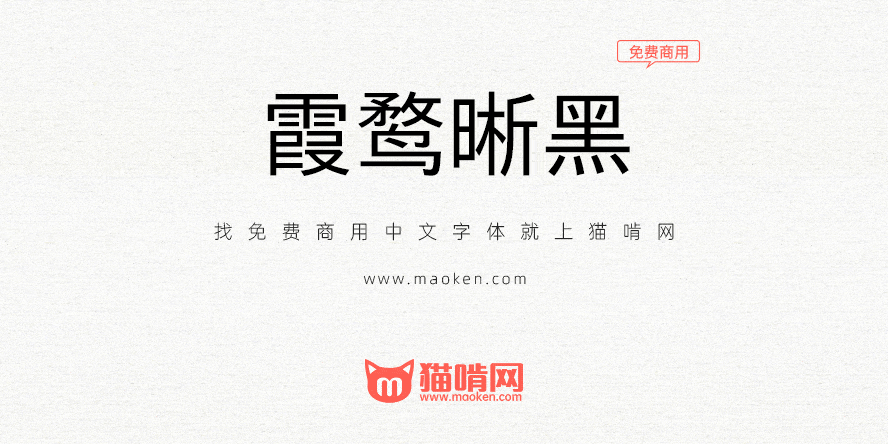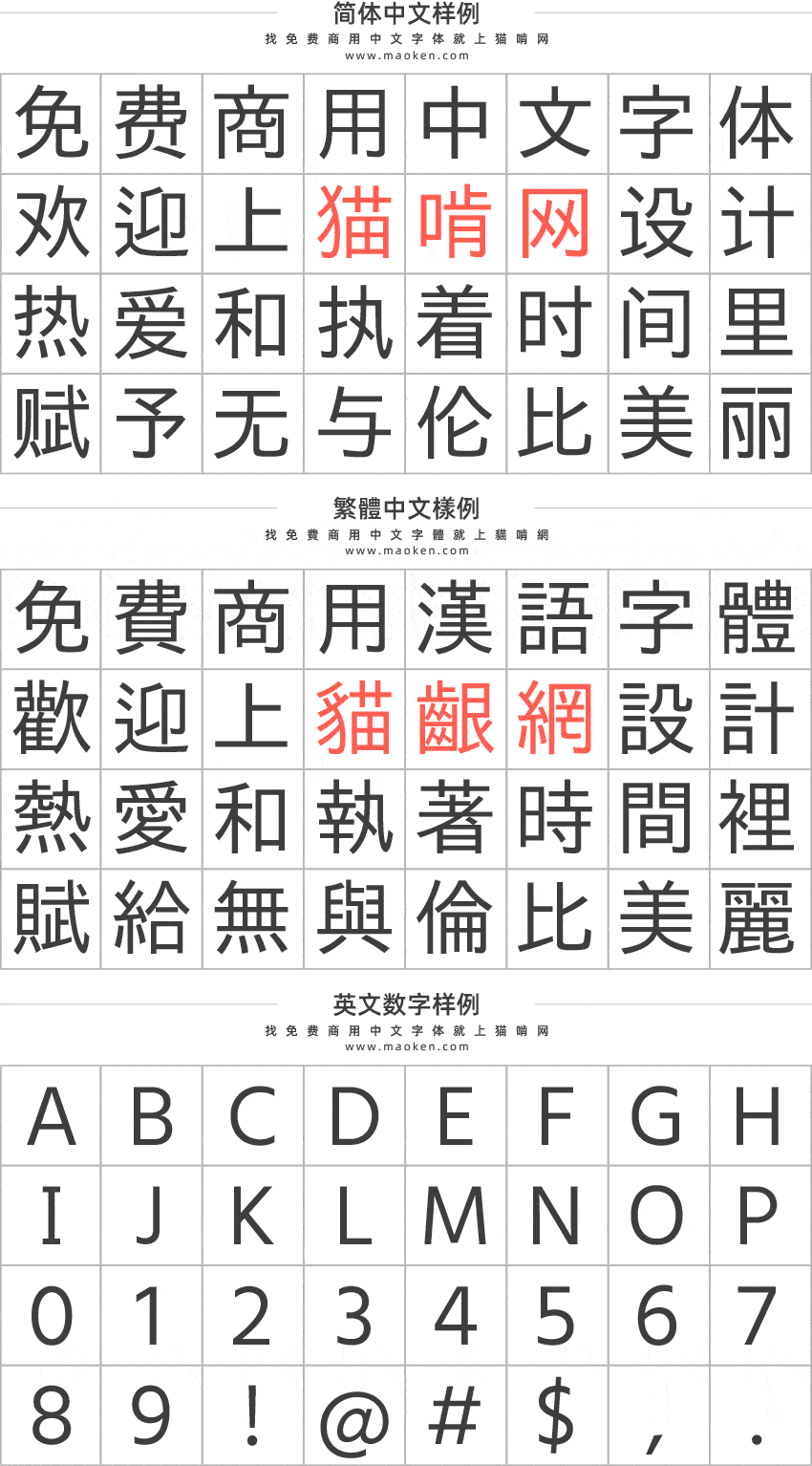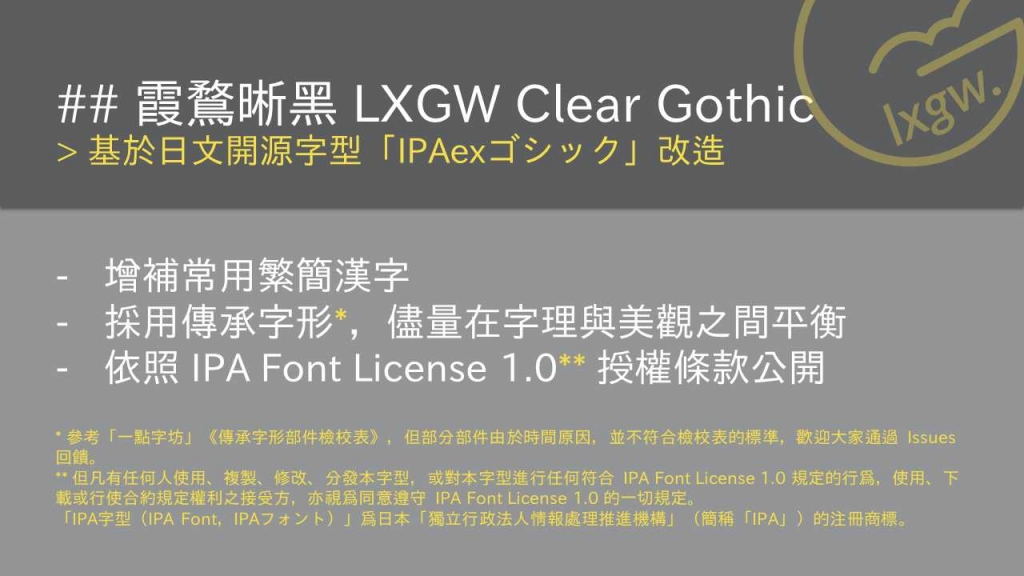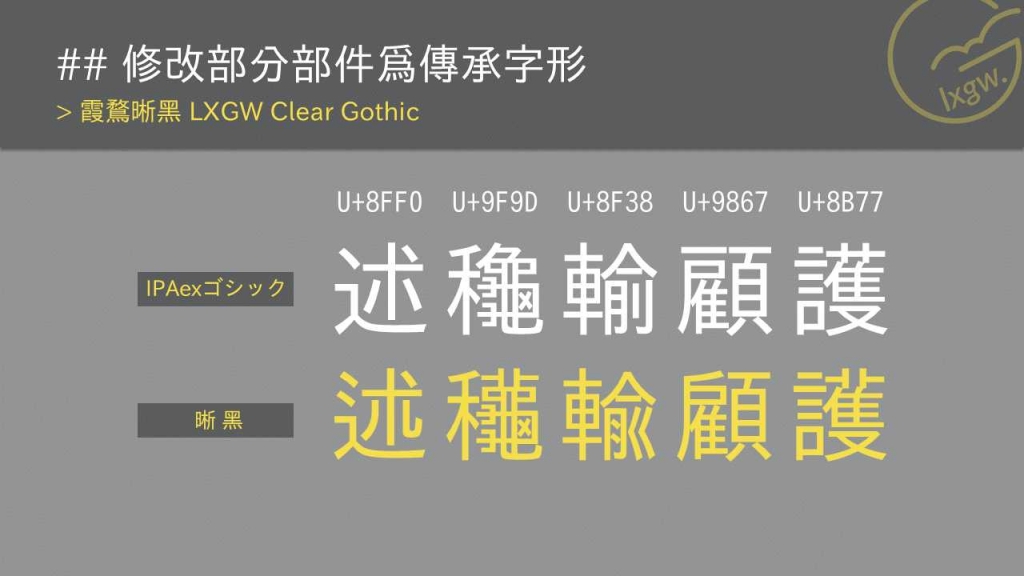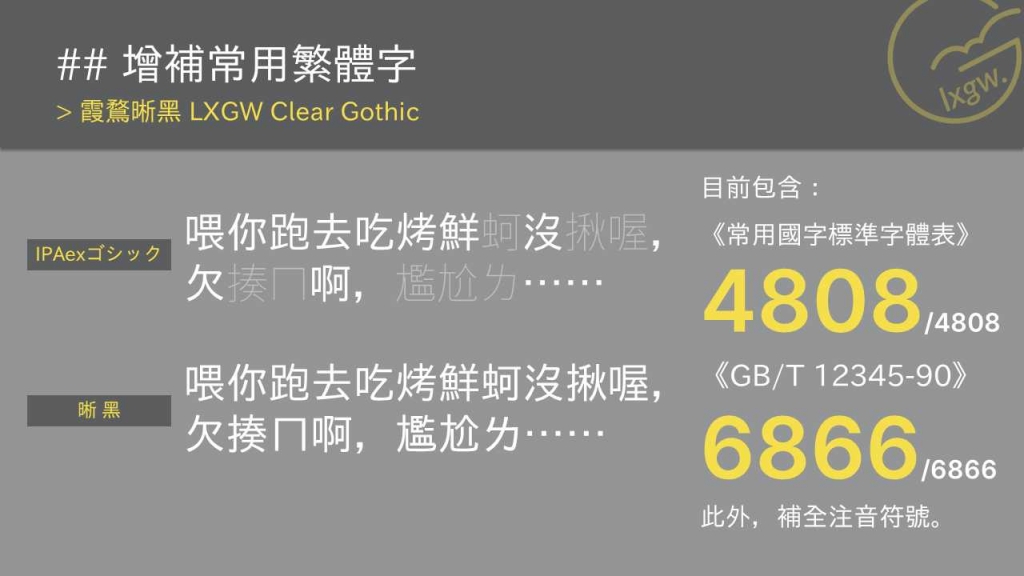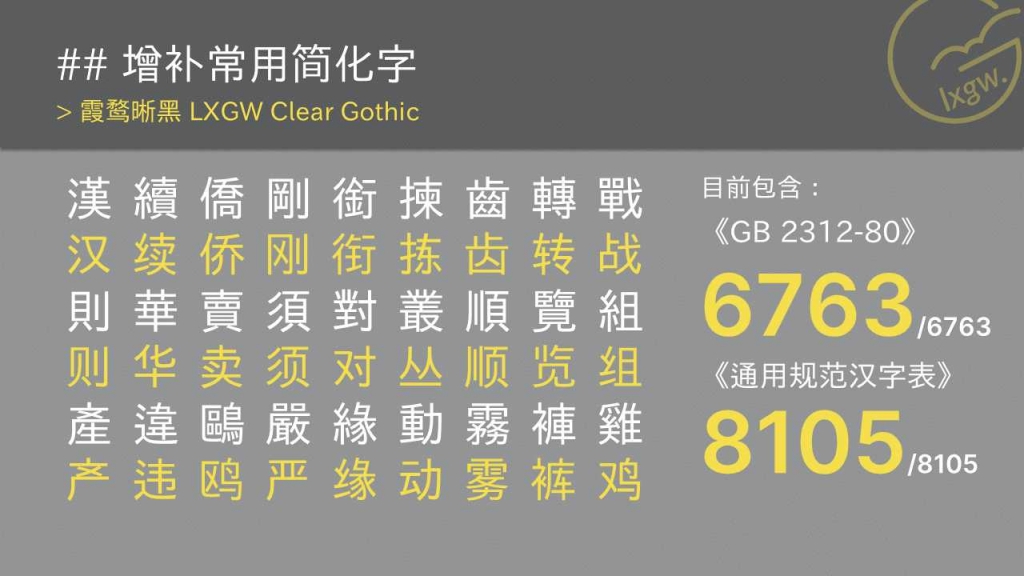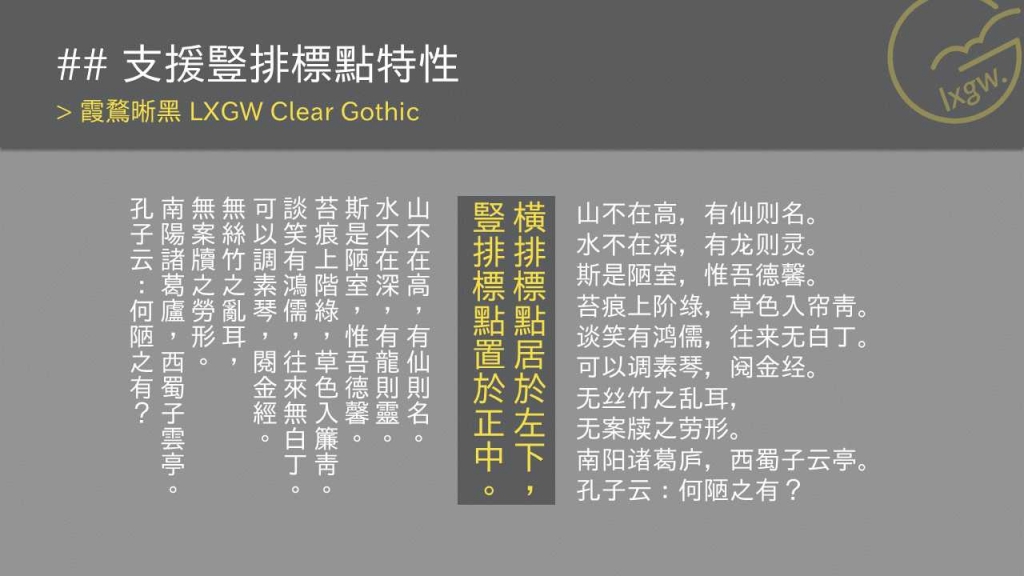
霞鹜晰黑:一款衍生于IPAex黑体的免费中文字体 更精致更清晰
一、项目简介
2009 年,日本IPA以符合Open Source Initiative开源定义的「IPA 开放字型授权条款」,发布两款「IPA 字体」,包括 「IPA 明体(IPA 明朝)」及「IPA 黑体(IPA ゴシック)」。字体衍生自林隆男(Takao Hayashi)所设计的两款字体:TypeBank 公司的「TB 明体」和「TB 黑体」。字体包含的日本常用的字符,供日本用户使用。
后来,经过多年的持续修补及修订,「IPA明体」扩充成 「IPAex明体」 、 「IPAmj明体」 。目前由「IPAmj明体」衍生的中文字体有很多,如「IPA 明体补字」、「南廱明体」「一点明体」 等,以适合中文使用环境。其中以「传承字型」为主的「一点明体」已将 常用繁体字、闽南语用字、客家语用字、粤语用字和 GB 2312 范围内的简化字补全。
而黑体部分,官方只扩充到了「IPAex黑体」。「IPAex黑体」的字数虽然已经满足日本人的需求,但要让它适用于中文,还有若干汉字要补全。而目前由「IPAex黑体」衍生的中文字体很少,而且缺少大量简体字和一部分常用繁体字。
(本人曾先后用方正悠黑和思源黑体将该字体补全作为手机字体,但是方正悠黑是版权字体,商用需要获得授权,而思源黑体补进去也有一定的违和感。)
鉴于此,也为了联动「一点明体」,本人开始了这个计划,将「IPAex黑体」补全常用简繁体汉字,使其适用于中文使用环境。
二、字体概况
本字体是 「IPAex黑体」 的中文化改造,在原「IPAex黑体」的基础上,利用原有的部件和笔形,对缺少的汉字进行补足。由于受到「一点明体」的影响,结合字体原有的风格,该字体做成了旧字形(其中一部分部件参考了「传承字形部件检校表」) (新字形请参阅霞鹜新晰黑 。目前已补全原字体中有对应繁体字的简体字、 GB 2312 范围内的所有汉字 (简体为主,6763 个) 、GB 12345 范围内的所有汉字 (繁体为主,6866 个) 、「通用规范汉字表」汉字 (简体为主,8105 个) 、台湾教育部门规定的 4808 个常用汉字,以满足繁简中文的一般使用需要。
由于该字体显示清晰,适合屏幕,故取名 「晰黑」 。包含两个字重:Regular、Book。Regular 为原字体的字重,Book 比 Regular 粗一些,更适合屏幕阅读。
• 修改下列汉字的写法:敷湧率薇繭夅降韋?曻桀桝偉傑粦舜葦違韌搩暐瑋禕僲粼舞褘隣嶙憐潾磔緯衛遴韑?儛燐璘膦諱辚瞬瞵磷闈韓韔?竵翷韘韙韞轔韛韜韡鏻鳞鱗麟炁既厩旣塈慨溉概槩墍漑槪簪蠶埖硴錵勗蘰枲乎呼烀轷虖軤嫭滹罅耗耕籍瓣廠廷侹娗庭挺?梃烶珽铤颋筳艇莛蜓鋌霆頲䗴鐵壬任妊纴饪紝衽飪凭姙恁赁䇮荏袵賃
• 修改下列汉字:侅俍偣傍僮僻刻劈劾咳唼啷啼喑嘀噇噫噺噼嚨垓埌境墒壁壟壠奒娘嫜嫡嬖孩孽宰寵峐崹嵭嶂幛幟幢廊彰徬徸意憧接揞揥摘撞擗擘攏敵新暗暲曈曨朖朗朧核梓椄楴榇榔榜樟樴橦檗櫬櫳欬歆毅氦浪渧滂滴漳潼澵澼瀧熵熾牓狼獐琅瑯璋璧瓏甓瞳矓磅礱禘稂穜競竸籑籠粮糵締織缔翣職聾膀臂艆艟薛薜薪蘖蜋螂螃蟑襞襯襲親該誏諦諳謗謫識譬讋该谙谛谤谪豅賅贛赅赣踉蹄蹢躄躘辜辞辟辣辤辦辧辨辩辫辭辮辯遧適避郎郞鄉鄣酿鋃鋅鍗鎊鏑鏡鏱鐘鐴鐾鐿锌锒镑镜镝镱閡閬闇阂阆障隴霎靇韴韵韶韻響駭騂骇骍骸鱆鶙鸊麞黯龐龔龕龗朗⾟⾳⿓⻯亥亲妾帝旁竞竟章童商啇啻良痎瘖瘴癖筤荄莘莨蒂蒡蕫。
• 调整西里尔字母的间距。
• 修改以下汉字:諮谘菡蒁邃螽啟啓肇顧綟綮僱冤鲷鯛亡忙妄忘盲網辋硭铓鋩步埗徏捗涉陟频踄頻骘騭贾賈槚檟價価璺爨釁臖亹绤綌渓鶏。
• 补全「通用规范汉字表」内的 8105 个汉字。
• IPA 版调整竖排标点符号为居中样式。
• IPA 版修改字母小写「l」与大写「I」区分。
• 新增注音符号(ㄅㄆㄇㄈ)。
• 修改以下汉字:眾潀聚驟鄹骤窗窻聰總驄蔥傯璁唳彫戻涙癒蘭骢
• 霞鹜晰黑第一版正式发布。
修正:環
啊有些字貌似还不是旧字形,例如关、刍、冗(及带此部件的字)、奥。
旧字形晰黑更新到 v0.204,新晰黑更新到 v0.223。
新晰黑已补完 GB2312,基本满足简体中文用字需要,下一步将补全通用规范汉字表。
新字型版晰黑正在制作中,初版将覆盖 3500 常用字。
• 初版(0.1)已经上传,包括「现代汉语常用字表」3500字、「义务教育语文课程常用字表」3000字,GB2312一级汉字3755个。计划将补全 GB2312 和通用规范汉字表。
但是有的字形不是傳承字形,更新後可能會有。
• 有些部件涉及到的字比较多,所以暂时没改。